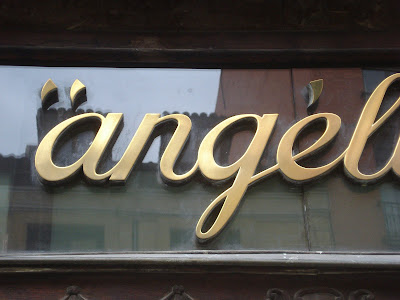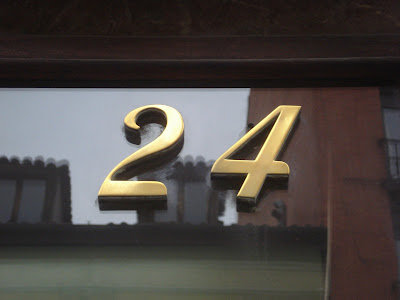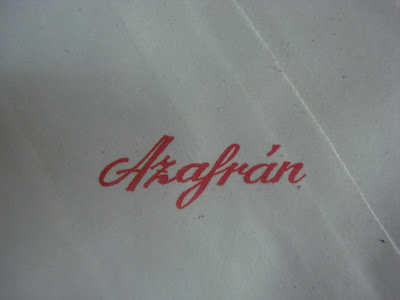
Herboristería Angélica
En la calle San Bernardo 24, abierta en 1948.
La tipografía del rótulo (en bronce sobre cristal) es también utilizada para toda la imagen gráfica de la tienda, desde el toldo a los sobres en los que despachan género (abajo, imágenes con el anverso y reverso de uno de ellos).